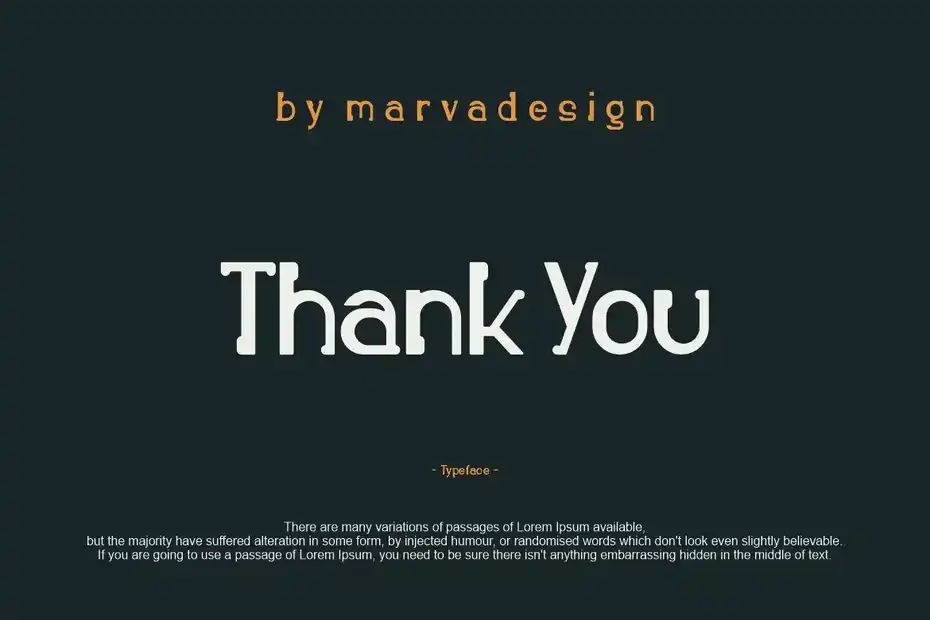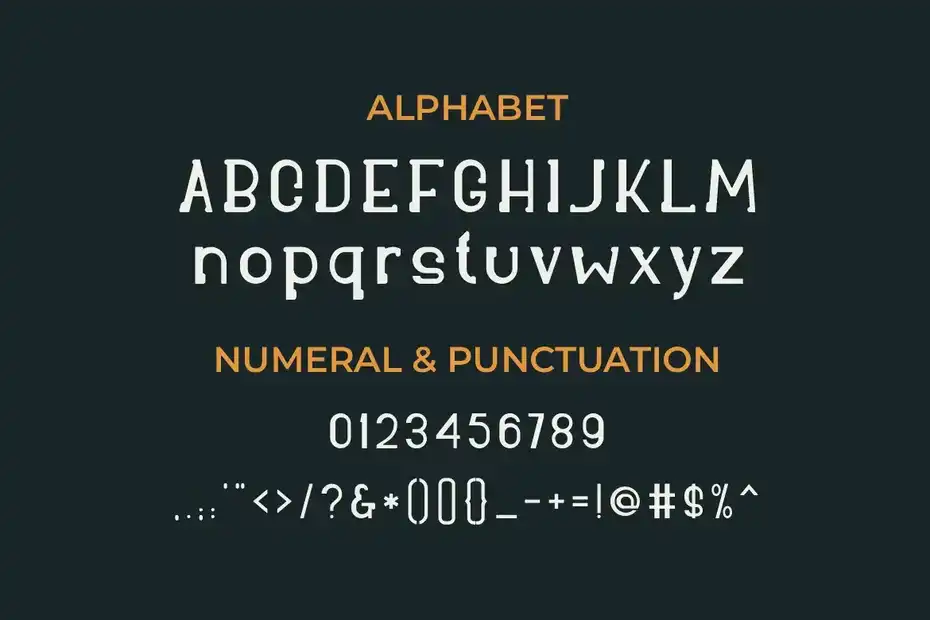
فونت انگلیسی Berned Font : این فونت یک فونت نمایشگر برجسته و معتبر است که برای پروژه های برندسازی مانند: لوگو، چاپ تیشرت، محصول و غیره مناسب میباشد.
- عنوان مجموعه: Berned Font
- سبک: Serif
- فضا بین حروف: معمولی